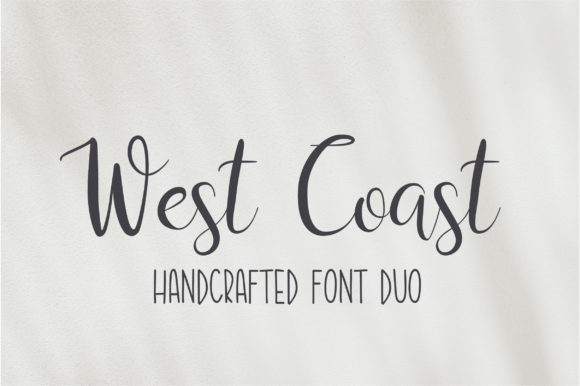
West Coast
West Coastのような高品質の素材をお探しの場合、このプレミアムパッケージはクリエイティブなプロジェクトに素晴らしい選択です。
精密に作られたWest Coastは、クリーンなベクター、滑らかなタイポグラフィ、そして安心のための商用ライセンスを提供します。
POD(オンデマンド印刷)製品、結婚式の招待状、またはソーシャルメディアのグラフィックを作成している場合でも、West Coastは理想的です。